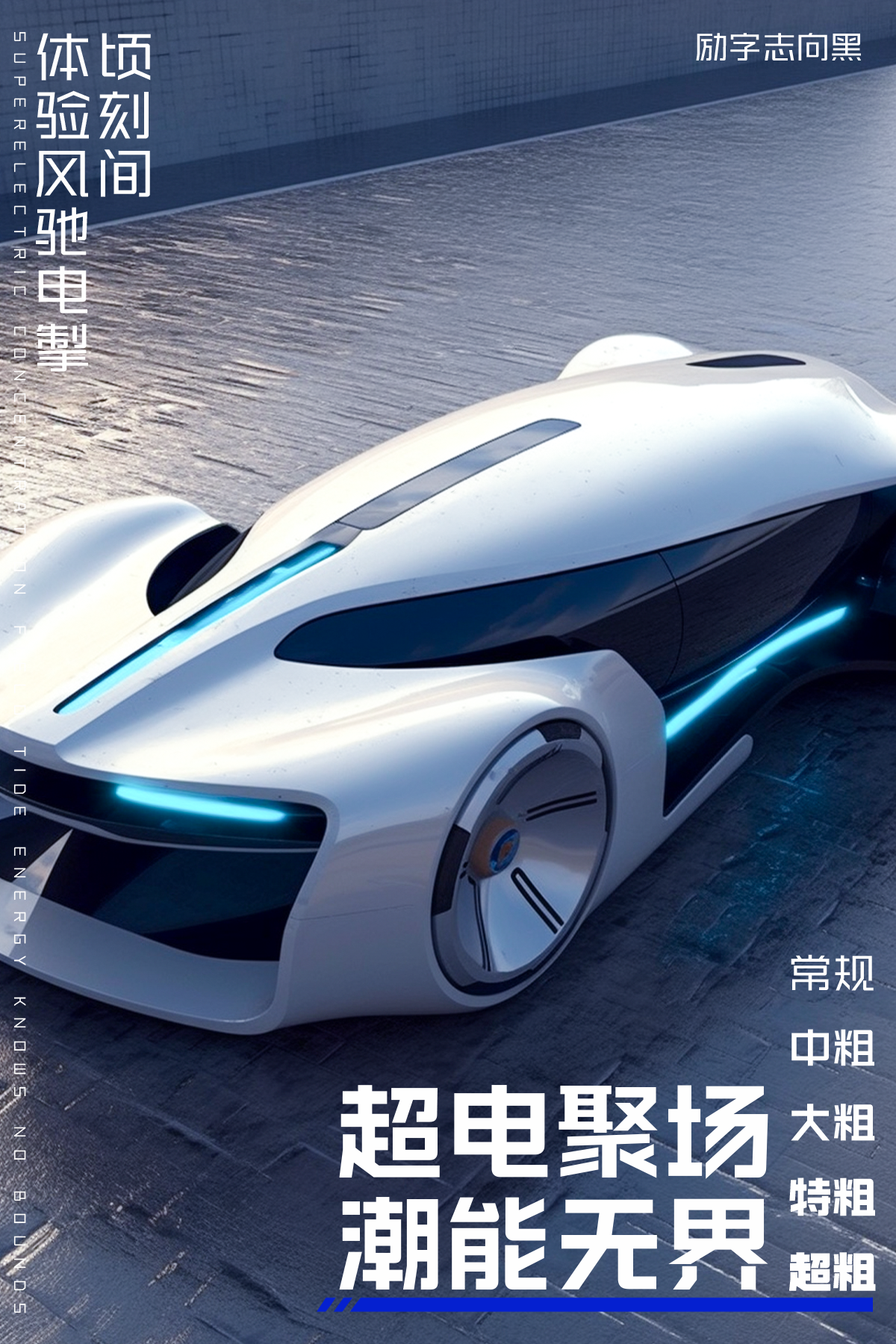
励字志向黑简 中粗
Dream-ZhixiangGB
字体名称:
励字志向黑简 中粗
字符集:
GB2312-1980
字体语言:
简体
书体类型:
黑体
字体类型:
普通字体
字体字重:
准黑(Medium)
志向黑采用圆体与黑体的融合,在笔画拐角增加适当的外圆角的手法在整体稳重大气的字形中增添少许灵动,使字体字面充实,结构稳定之余,更适配屏显的使用。